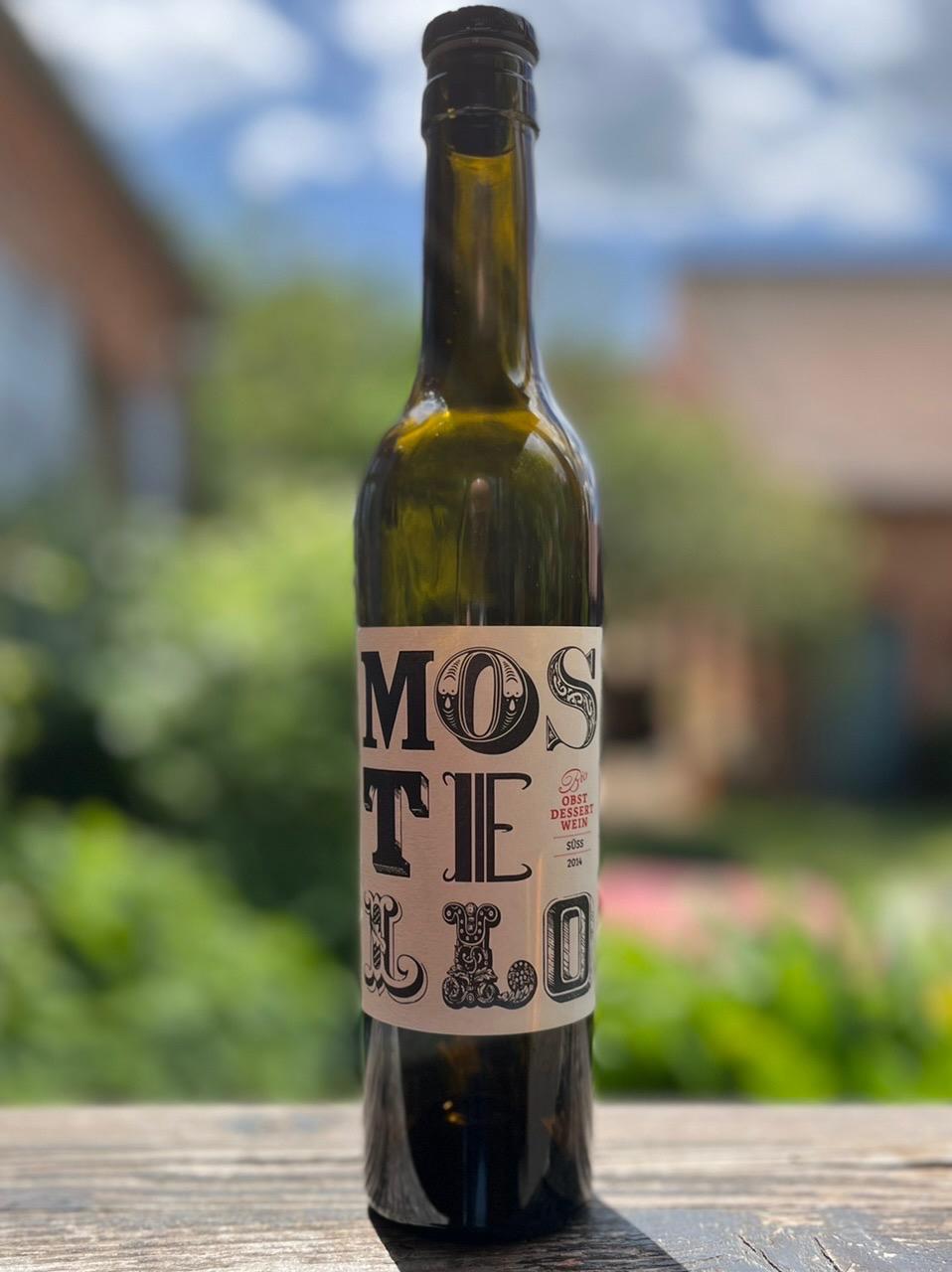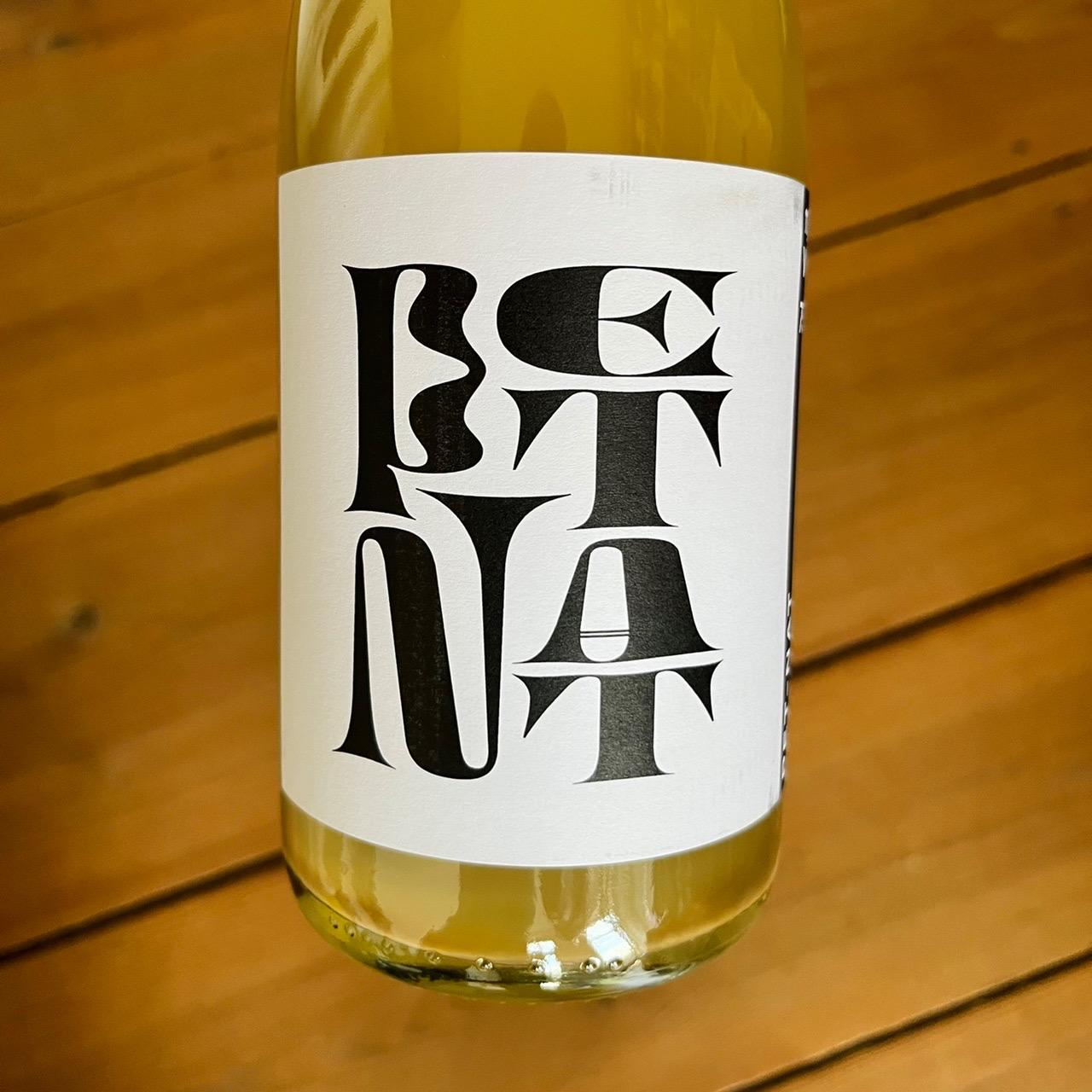
Das hat System …
… auch wenn’s mir nicht gefällt.
Gerade im Weinladen um die Ecke erworben … :rockon:
Ich kann‘s nicht lesen :-?Und da ich keine Ahnung von Weißwein habe, erschließt sich mir das auch nicht …
Ich mag es … und ich denke es passt in gewisser Weise auch zum Produkt. :-P
Hmm, spricht das für den Wein 🤔 Dass er irgendwie wackelig und undefiniert durcheinander ist :-?
"PetNat" ist erklärungsbedürftig, das erschließt sich ohne Recherche keinem. Auch "Skin" konnte ich noch nicht mal lesen, geschweige denn irgendeine Intention dahinter sehen.
Gestalterisch hätte ich das eher einem Discounter-Wein zugeordnet, keinem für 30 € die Flasche.
Das ist ein Hipster-Design, da ist jeder Preis möglich 🤣
Man kann das wackelig und undefiniert nennen — ich würde eher sagen verspielt & expressiv. Die Schrift wird hier zum Bild und das passt durchaus zum Wein. Da solche Weine nicht beim Discounter stehen sondern im gut sortierten Weinhandel sehe ich da auch kein Problem. An der Seite des Etiketts steht übrigens alles auch noch einmal klassisch für die Freunde aufgeräumter und vorrangig informativer Typografie.
Es gibt sicher viele höherpreisige Weine die mit Goldfolie und klassischen Schriften verpackt werden. Gerade jüngere Winzer gehen aber durchaus andere Wege und arbeiten mit verschiedensten grafischen Lösungen — von Mustern über Bilder oder eben »Typoexperimente«. Letztendlich gehts beim Packaging auch um Aufmerksamkeit und das funktioniert bei obigem Etikett zumindest bei mir sehr gut.
Gutes Design heißt für mich nicht "Goldfolie und klassische Schriften". Aber eben auch nicht "unleserlich und Rot-Grün-Farbverlauf". Da gibt es mit grafischen Lösungen oder eben Typoexperimenten auch Gelungenes.
Ich glaube jetzt vermischen sich die Aussagen. Du hattest gesagt, dass du die Gestaltung keinem 30-Euro-Wein zuordnen würdest. Aus meiner Erfahrungen arbeiten aber sehr viele der höherpreisigen Weine mit sehr klassischen und leider oft auch langweiligen Lösungen. Gutes Design hat nicht unbedingt etwas mit dem Preis zu tun bzw. ist teuer leider nicht zwangsläufig gut gestaltet.
Aber wir müssen das auch nicht weiter ausdiskutieren. Ich halte einfach fest, dass dir das besagte Etikett weniger gefällt als mir. Die Gründe sind am Ende subjektiv.
Abgesehen von der Lesbarkeit und den gewählten Begriffen, fand ich das mal ein durchaus nachvollziehendes und erfrischendes Konzept für eine alkoholische Flüssigkeit mit Rauschpotential. Bei einem höherprozentigen Getränk hätte es vielleicht noch besser gepasst. ;-)
Deswegen hätte ich das eher Richtung Discounter-Fusel verortet. Winzer, die hochpreisige Weine herstellen, haben nicht den Rausch im Sinn, sondern hunderte andere Beweggründe.
Was ich ja auch gutheiße, an Goldfolie und klassische Schriften haben sich die meisten wohl wirklich sattgesehen. Es gibt ja genügend positive Beispiele. Aber, wie Microboy schon angemerkt hat, das ist alles subjektiv.
Sind im Endeffekt auch nur andere Begriffe für das, was ich meinte. Und auf Wein bezogen, kann ich mir da gar nix drunter vorstellen bzw wäre da für mich verspielt & expressiv [sic] irgendwie undefiniert. Aber wie gesagt: Mit Weißwein kenne ich mich nicht aus, da bekomme ich vom ersten Schluck Schädelbrummen (manchmal reicht es schon, wenn ich die Flasche sehe).
Dass der eher im sortierten Weinhandel zu finden ist, war mir schon klar; völlig ungelungen finde ich die Gestaltung auch gar nicht, wenn man den schwarzen Streifen mit lesbarerer Schrift mit einbezieht. Ich fragte mich nur, wie so eine Gestaltung tatsächlich den Charakter des Weines wiedergegeben kann :-?
p.s.: Wenn überhaupt Alkohol, dann ein guter, ehrlicher Roter – im Sommer gerne mal etwas frischer/fruchtiger, ansonsten trocken und erdige Eiche 😋
Das, und es gibt genug Weine, wo die Goldfolie das wertvollste ist und diese dadurch keine Auszeichnung mehr darstellt.
Gar nicht wegen der Typografie, aber weil es thematisch so gut passt: Das neue Bier der finnischen Brauerei Olaf aus Savonlinna. (Kommt mit der Produktion nicht mehr nach …)